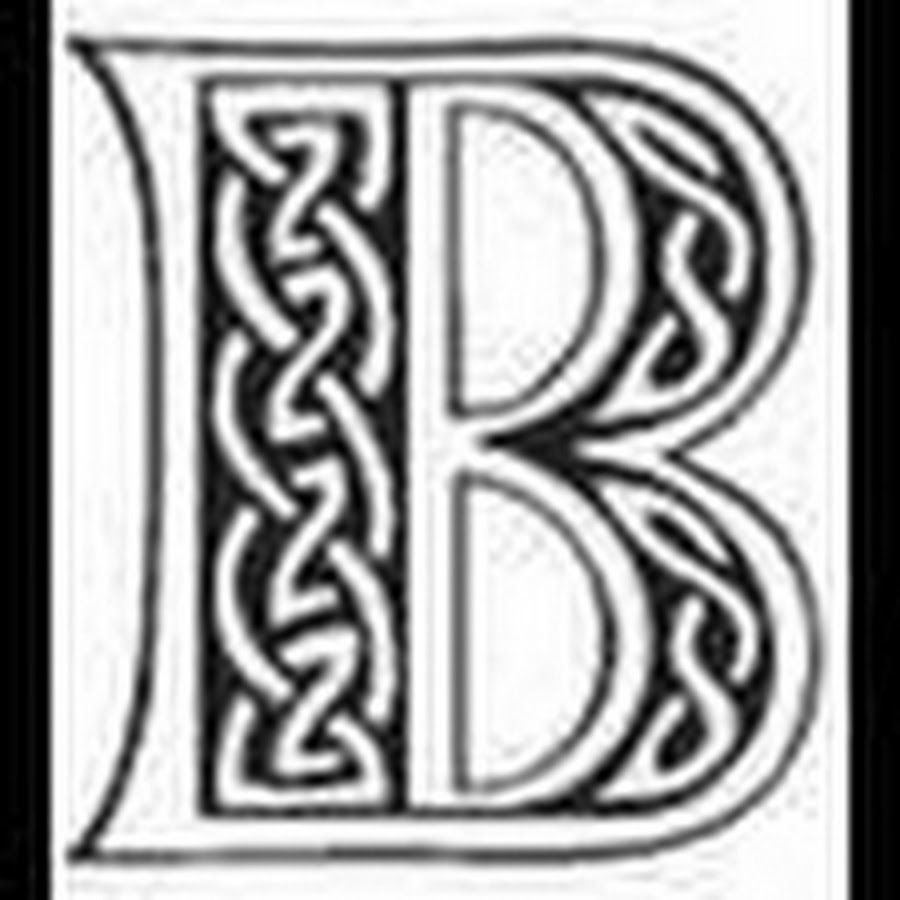
Кельтские символы.
— Кельтские символы. Оказывается, есть способ добавить стилизованные буквы, которые на самом деле являются специальными символами,
Кельтские символы.
- Гэльские скриптовые шрифты SMO Gaelic College
- Гэльский и огамский гарнитуры доктора Берлина
- Клофуарн Огайм Огам Шрифты